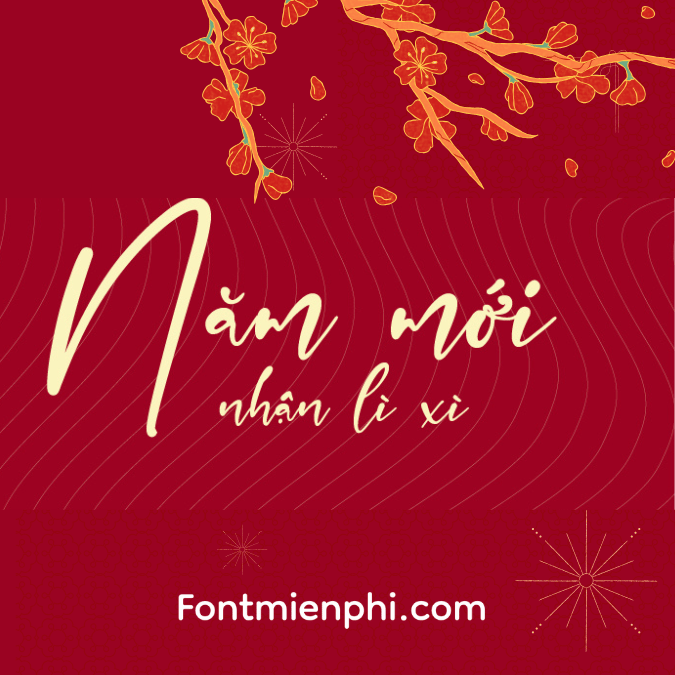
Font Việt hóa 1FTV VIP Smithen Goulding ,font Tết
FONT VIỆT HÓA 1FTV VIP SMITHEN GOULDING
“Đẳng cấp Typography từ London”
ĐẶC ĐIỂM NỔI BẬT
Phong cách British Elegance: Nét chữ Serif hiện đại pha chất cổ điển Anh Quốc
✒️ Độ tương phản ấn tượng: Tỉ lệ nét thanh – đậm được cân chỉnh hoàn hảo
Tối ưu đa ngữ: Full bộ dấu tiếng Việt + bộ ký tự Latinh mở rộng
ỨNG DỤNG CAO CẤP
• Nhận diện thương hiệu thời trang cao cấp
• Tạp chí phong cách sống đẳng cấp
• Bao bì sản phẩm hạng sang (rượu whisky, đồ da)
• Thiết kế đồ họa cho khách sạn 5 sao
BỘ VIP “SAVILE ROW”
4 phiên bản độc quyền:
• Regular (nét chuẩn)
• Italic (nét nghiêng quý phái)
• Condensed (phiên bản thu gọn)
• Shadow (hiệu ứng bóng đổ)
“Smithen Goulding – Phong cách Anh Quốc đích thực trong từng con chữ”